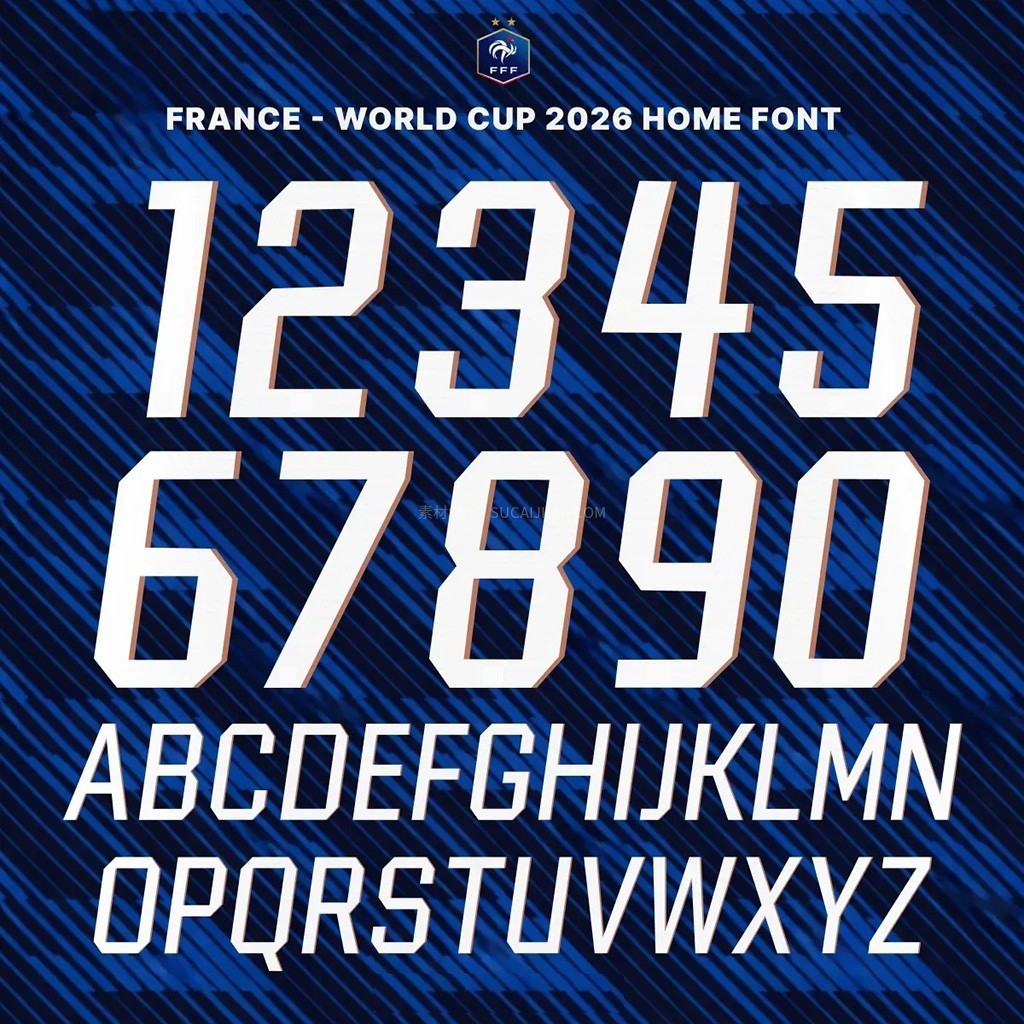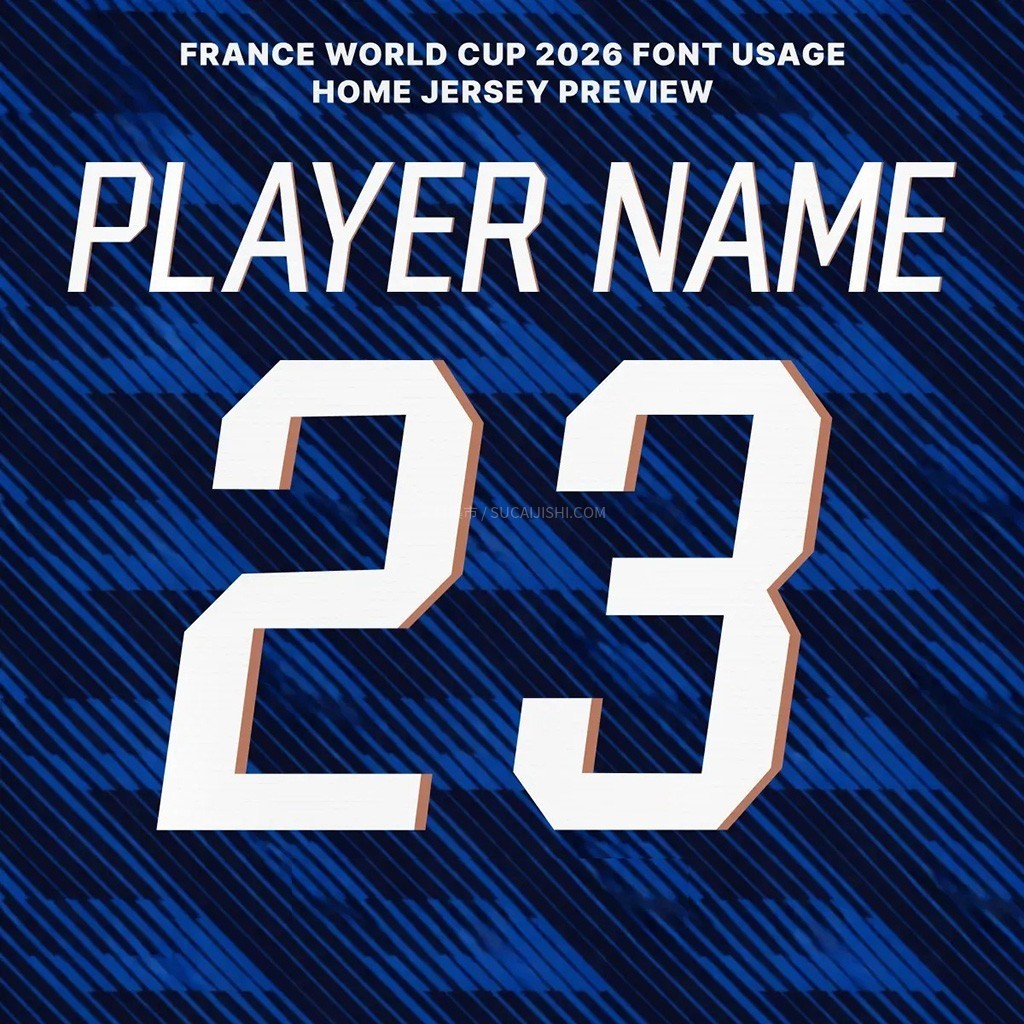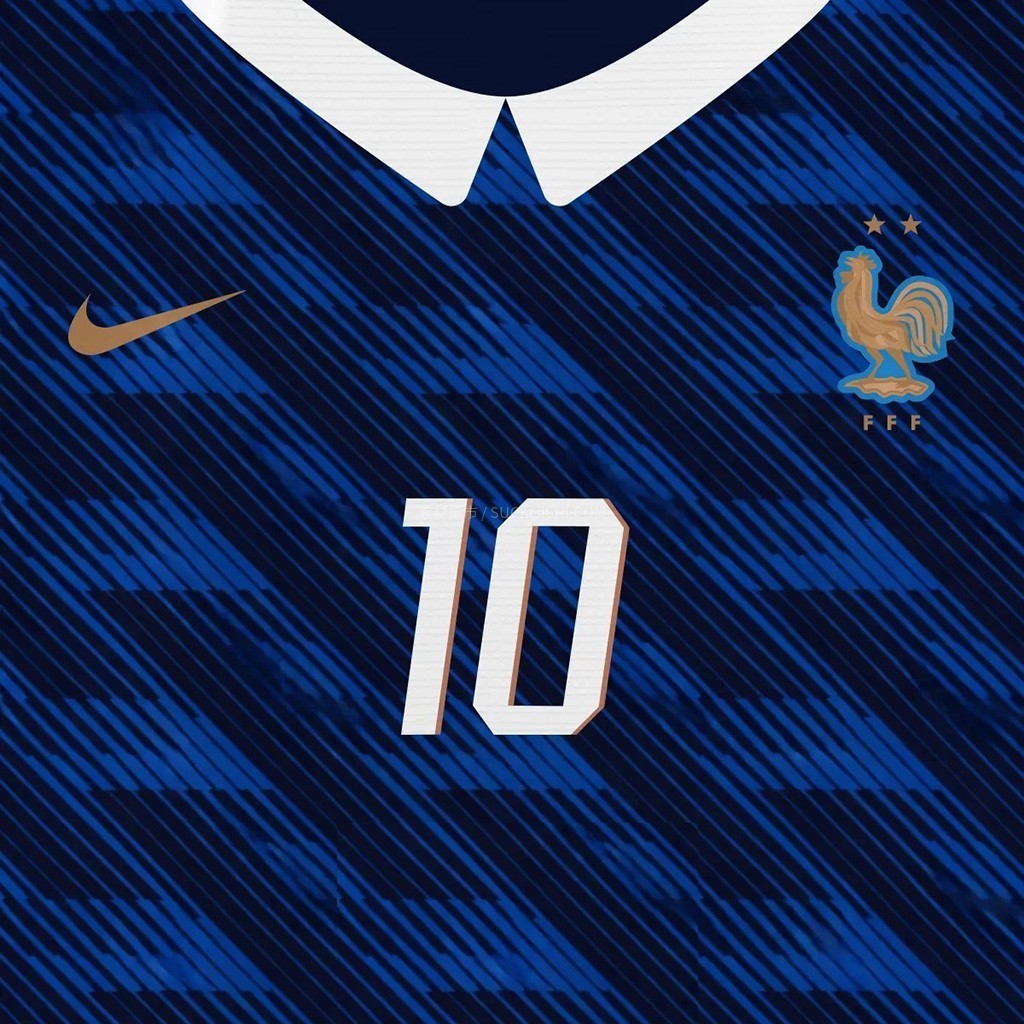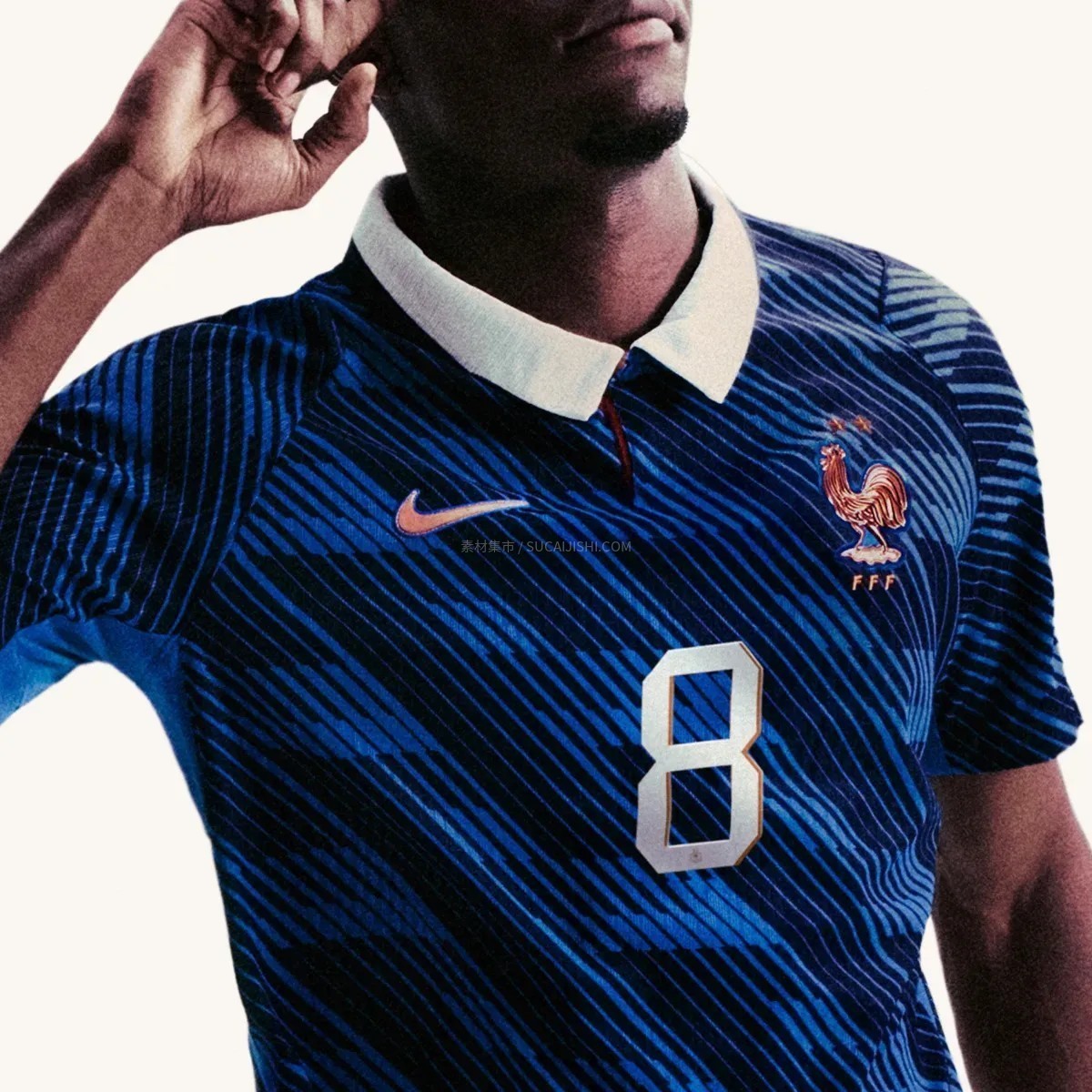
法国2026世界杯主场球衣字体
很少有国家队能像法国队一样,在国际大赛中展现出如此强大的视觉统治力!这款 2026 年法国世界杯主场字体套装,完美复刻了法国队在北美冲击第三座大力神杯时所使用的球衣字母与号码。每个字符都经过精细考究,完美还原球场上真实的比例、笔画粗细和字间距。随着姆巴佩、登贝莱和萨利巴等巨星领衔出征,这套伴随标志性深蓝战袍的字体已经引爆全球设计圈与球迷圈。快来收下这款专属资源,为你的体育视觉设计注入满满的冠军基因!